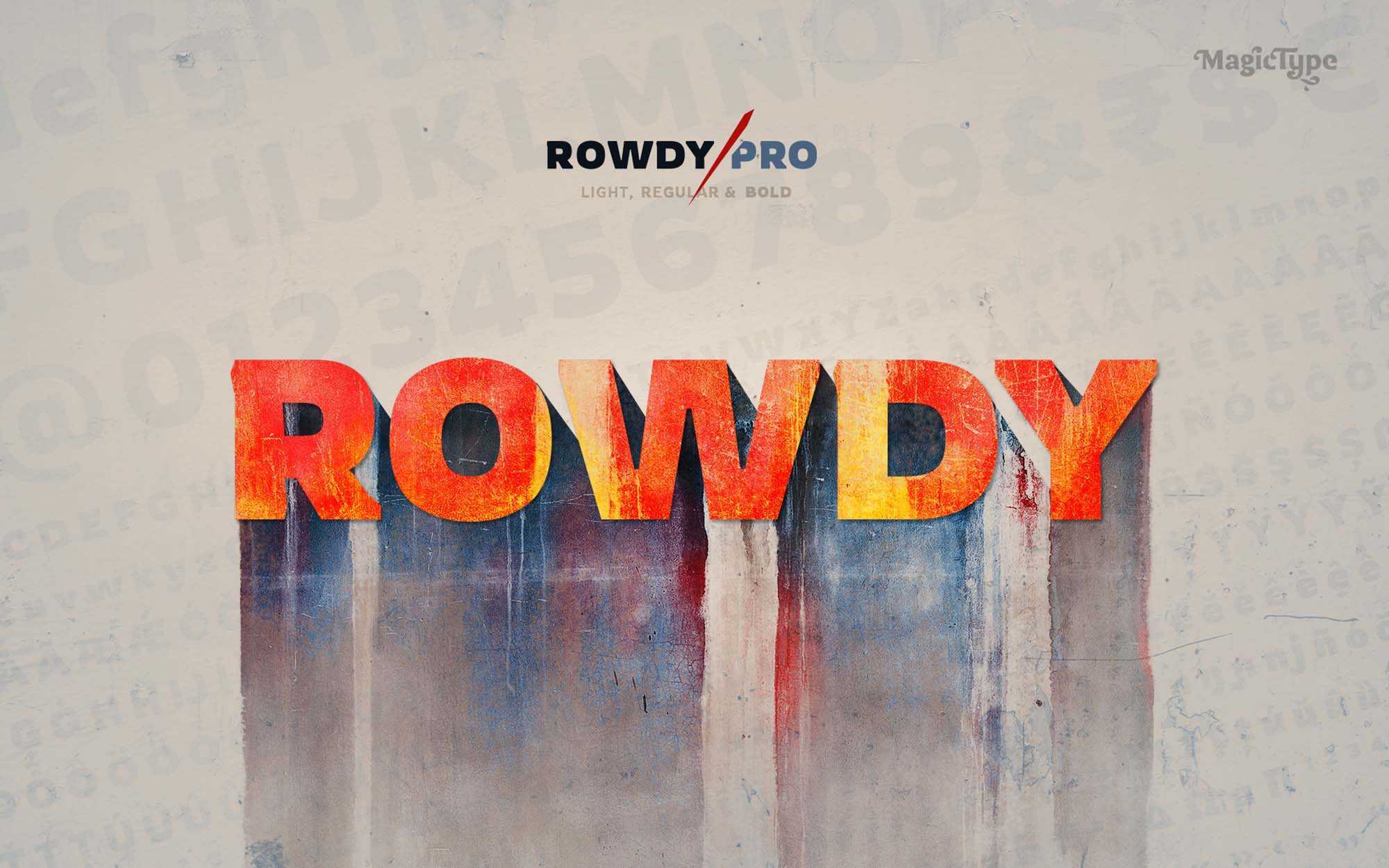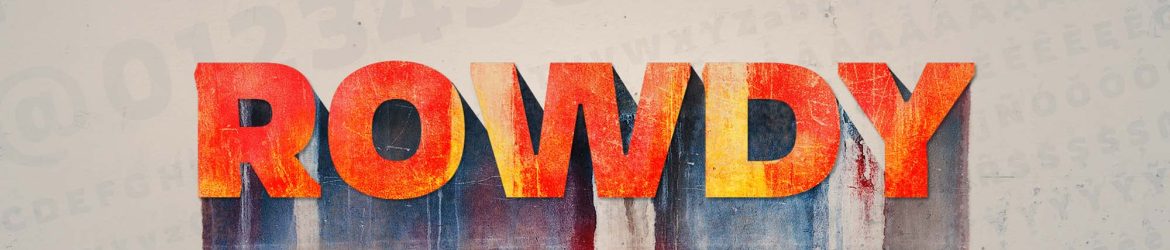
Rowdy Latin Display Typeface – Download Grátis
Prepare-se para ser conquistado por essa fonte! O Rowdy é um tipo de letra latino dominante e chamativo em três pesos de fonte diferentes. Inspirado por um período marcado pela agressividade do cinema de ação indiano, esse tipo de letra é uma escolha sólida para headlines que significam algo. Suas linhas afiadas e largura ótima dos caracteres tornam a fonte perfeita para anúncios e títulos. Para invocar confiança, nada melhor do que usar uma fonte ideal para posters, gráficos grandes e desenhos de camisetas.